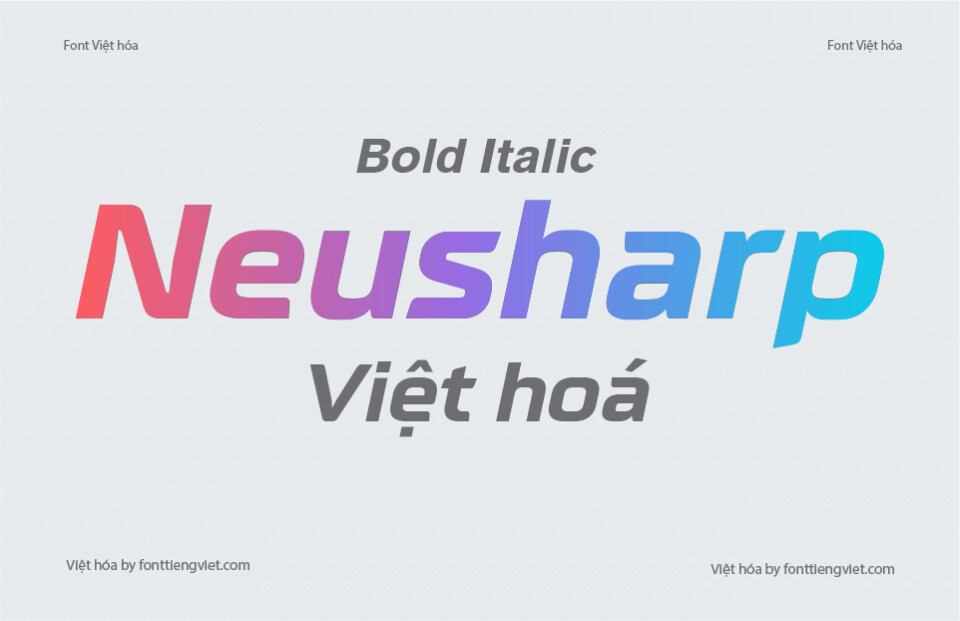
Font Việt hóa 1FTV VIP Neusharp Bold Italic
Trong thế giới đồ họa hiện nay, việc lựa chọn một bộ Font Miễn Phí chất lượng và phù hợp với ngữ cảnh là yếu tố then chốt tạo nên sự thành công cho mọi tác phẩm. Font Việt hóa 1FTV VIP Neusharp Bold Italic nổi lên như một giải pháp hoàn hảo dành cho những ai đang tìm kiếm sự mạnh mẽ, bứt phá và mang hơi hướng tương lai. Đây là một phông chữ thuộc phong cách sans-serif hiện đại, được tối ưu hóa hoàn toàn cho tiếng Việt, giúp các bạn học sinh, sinh viên và các nhà thiết kế tự do dễ dàng tiếp cận mà không lo lỗi font hay thiếu dấu. Với đường nét sắc sảo và độ nghiêng đặc trưng, bộ font này chắc chắn sẽ làm nổi bật mọi thông điệp truyền tải.
Đặc điểm nổi bật của Font Việt hóa 1FTV VIP Neusharp Bold Italic
Lý do khiến Font Việt hóa 1FTV VIP Neusharp Bold Italic trở nên phổ biến chính là nhờ cấu trúc hình học chuẩn xác và phong cách thể thao đầy năng lượng. Chữ “Neusharp” vốn nổi tiếng với các góc cạnh được xử lý tinh tế, tạo cảm giác chuyên nghiệp và chắc chắn. Khi kết hợp với định dạng Bold (đậm) và Italic (nghiêng), nó mang lại một hiệu ứng thị giác mạnh mẽ, thúc đẩy sự chuyển động và tốc độ. Điều này rất phù hợp cho các tiêu đề báo chí, bìa sách giáo khoa hiện đại hoặc các banner cổ động trong trường học.
Khả năng ứng dụng đa dạng trong giáo dục và thiết kế
Đối với các bạn học sinh, việc sử dụng Font Việt hóa 1FTV VIP Neusharp Bold Italic trong các bài thuyết trình PowerPoint hay báo cáo dự án sẽ giúp bài làm trở nên thu hút và chuyên nghiệp hơn. Trong môi trường sư phạm, thầy cô có thể dùng font chữ này để thiết kế các bảng tin, khẩu hiệu thi đua hoặc bằng khen cho học sinh. Nhờ tính năng Việt hóa chuẩn từ đội ngũ 1FTV, mọi ký tự như “ă”, “â”, “đ” hay các dấu thanh đều được căn chỉnh tỉ mỉ, đảm bảo sự đồng nhất và dễ đọc trên cả màn hình kỹ thuật số lẫn bản in giấy.
Tối ưu hóa hiển thị và trải nghiệm người dùng
Không chỉ dừng lại ở vẻ ngoài ấn tượng, Font Việt hóa 1FTV VIP Neusharp Bold Italic còn được đánh giá cao về độ tương phản. Khoảng cách giữa các chữ cái (kerning) được thiết lập hợp lý, giúp văn bản không bị dính chữ dù ở kích thước nhỏ. Đặc biệt, định dạng Bold Italic giúp tạo điểm nhấn tức thì cho những từ khóa quan trọng trong đoạn văn, hỗ trợ người đọc dễ dàng nắm bắt nội dung cốt lõi. Đây là một công cụ hỗ trợ đắc lực cho việc truyền đạt thông tin một cách mạch lạc và thẩm mỹ.
Kết luận về bộ font chữ độc đáo
Hy vọng rằng bộ Font Việt hóa 1FTV VIP Neusharp Bold Italic sẽ là nguồn cảm hứng mới cho các dự án sáng tạo của bạn. Sự kết hợp giữa nét chữ đậm khỏe khoắn và độ nghiêng tinh tế mang lại một phong cách cá tính mà hiếm bộ font nào có được. Đừng quên truy cập thường xuyên để cập nhật thêm nhiều bộ Font Miễn Phí, Font Việt Hóa, Font Việt hóa 1FTV VIP Neusharp Bold Italic độc đáo khác phục vụ cho học tập và công việc. Chúc bạn có những trải nghiệm thiết kế tuyệt vời và đầy ấn tượng với bộ phông chữ đặc biệt này!